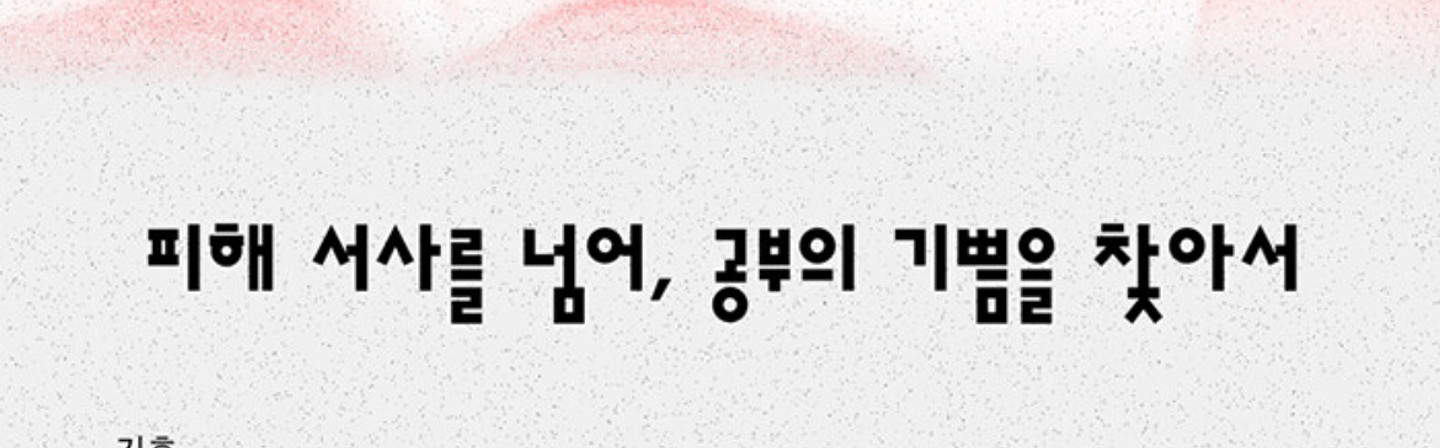
어플 데일리노트 에서 선택 가능한 폰트인데, 뭔지 알수가 없어서 들고왔습니다 최대한 폰트 특징을 알 수 있도록 떠들어봤습니다.. 히읗이랑 온점, ㅋㅋ 의 세로획이 살짝 휘었다는 것 요정도가 특징같은데 여기저기 고딕을 뒤져봐도 뭔지 모르겠어요 폰트천재님들 도와주십쇼!!!!!!! 너무 궁금해서 개발자 메일로 문의도 넣었는데 당연하게도(당연한가?) 읽씹해서두번 보내긴 기분이 상하네요,, 껄껄 + 아래에서 비슷한 폰트를 찾았는데 윤고딕100도 아닌것같아요 🤔
Gothic A1 (주)한양정보통신